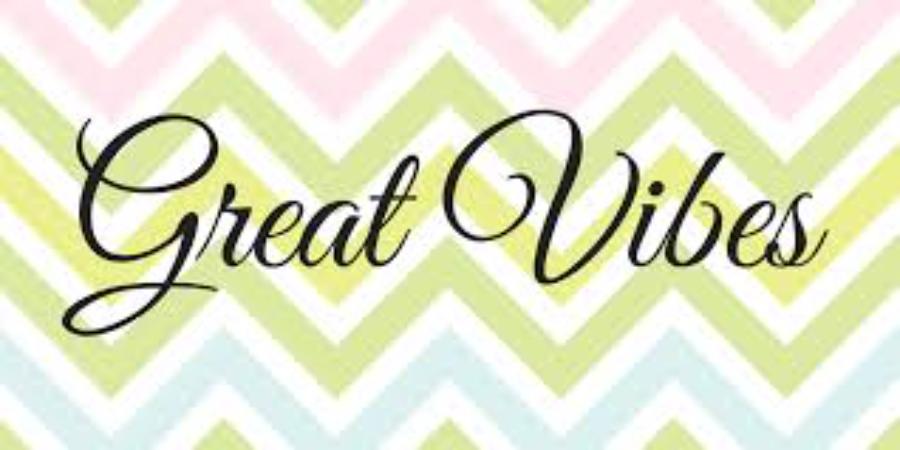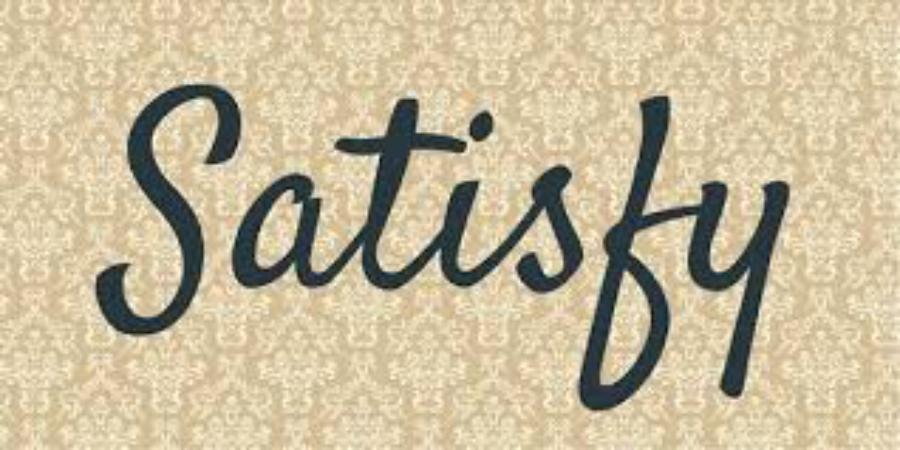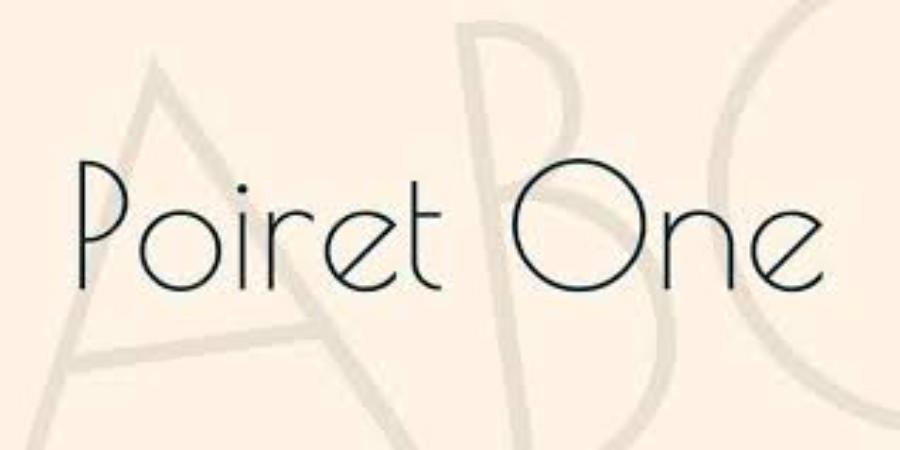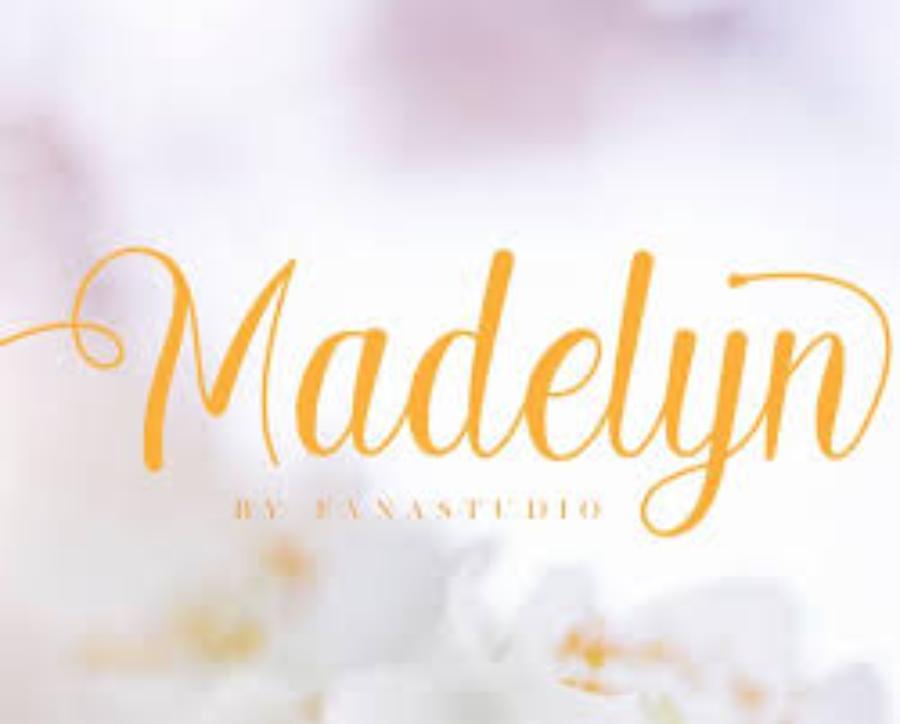
Danh Sách 10 Font Chữ Calligraphy Miễn Phí Bạn Không Thể Bỏ Qua
Danh sách 10 font chữ Calligraphy miễn phí và đẹp mắt cho các designer. Hãy tìm hiểu cách chúng có thể làm phong phú thêm các dự án thiết kế của bạn tại SaDesign.
Lựa chọn font chữ phù hợp là một yếu tố quan trọng quyết định đến tính thẩm mỹ và hiệu quả truyền tải thông điệp trong lĩnh vực thiết kế đồ họa. Font chữ Calligraphy, với vẻ đẹp thanh thoát và sự mềm mại trong từng nét chữ, từ lâu đã trở thành một lựa chọn yêu thích của các designer. Bài viết sau, Sadesign sẽ giới thiệu 10 font chữ Calligraphy miễn phí mà bất kỳ designer nào cũng không thể bỏ qua, giúp bạn tạo ra những tác phẩm thiết kế ấn tượng và chuyên nghiệp hơn.
1. Font chữ Calligraphy là gì?
Font chữ Calligraphy là những kiểu chữ lấy cảm hứng từ nghệ thuật thư pháp, với nét chữ mềm mại, thanh thoát, đầy tính nghệ thuật và trang nhã. Những font chữ này thường được sử dụng trong các dự án thiết kế mang tính trang trọng, lịch lãm như thiệp cưới, thiệp mời, logo, hay các ấn phẩm quảng cáo cao cấp. Một font chữ Calligraphy đẹp không chỉ mang đến sự tinh tế cho thiết kế mà còn giúp truyền tải cảm xúc mạnh mẽ đến người nhìn.
Font chữ Calligraphy không chỉ dừng lại ở những tác phẩm thủ công mà giờ đây, với sự phát triển của công nghệ, các designer có thể dễ dàng áp dụng các font chữ Calligraphy này trong các phần mềm thiết kế như Adobe Illustrator, Photoshop, hay các nền tảng thiết kế online.
2. Top 10 Font chữ Calligraphy miễn phí không nên bỏ qua
Mặc dù có rất nhiều lựa chọn font chữ Calligraphy trên thị trường, nhưng không phải tất cả đều miễn phí. Trong bài viết này, chúng tôi sẽ giới thiệu 10 font chữ Calligraphy miễn phí mà mọi designer đều nên biết.
2.1. Pacifico
Pacifico là một font chữ Calligraphy rất phổ biến với các đường nét mềm mại, uốn lượn tự nhiên. Được thiết kế bởi Vernon Adams, Pacifico có phong cách dễ tiếp cận và rất thích hợp cho các thiết kế mang tính sáng tạo, vui tươi. Font chữ này thường được sử dụng trong các dự án liên quan đến thương hiệu thời trang, quà tặng, và các sản phẩm nghệ thuật.
Ưu điểm:
• Dễ đọc và linh hoạt khi sử dụng.
• Thích hợp cho các thiết kế hiện đại, trẻ trung.
2.2. Great Vibes
Great Vibes là một font chữ Calligraphy tuyệt đẹp với những đường cong mượt mà, thanh thoát. Nó mang đến vẻ đẹp sang trọng và trang nhã, hoàn hảo cho các dự án như thiệp mời, thiết kế logo, hay các ấn phẩm in ấn cao cấp. Great Vibes có sự kết hợp hoàn hảo giữa tính thẩm mỹ và sự dễ đọc, phù hợp với nhiều loại thiết kế khác nhau.
Ưu điểm:
• Phù hợp với các thiết kế sang trọng, quý phái.
• Có thể sử dụng cho nhiều loại dự án khác nhau.
2.3. Allura
Font chữ Allura nổi bật với những nét chữ mềm mại, thanh thoát, mang lại cảm giác rất dễ chịu khi đọc. Sự đơn giản nhưng vẫn đầy tinh tế của Allura làm cho nó trở thành một lựa chọn tuyệt vời cho các dự án cần sự trang nhã mà không quá cầu kỳ. Allura thường được sử dụng trong các ấn phẩm như banner, tờ rơi, hay các thiết kế thương hiệu cần sự lịch lãm.
Ưu điểm:
• Dễ sử dụng và tương thích tốt với các thiết kế website.
• Mang lại vẻ ngoài thanh lịch cho mọi dự án.
2.4. Dancing Script
Dancing Script là một font chữ Calligraphy với phong cách vui tươi, năng động. Những đường nét uốn lượn của Dancing Script khiến nó trở thành lựa chọn lý tưởng cho các thiết kế mang tính cá nhân, sáng tạo và gần gũi. Bạn có thể sử dụng Dancing Script cho các thiết kế như logo, slogan hay quảng cáo sản phẩm.
Ưu điểm:
• Phong cách trẻ trung, linh hoạt.
• Dễ dàng kết hợp với các kiểu chữ khác trong thiết kế.
2.5. Satisfy
Satisfy là một font chữ Calligraphy miễn phí khác, với phong cách mượt mà và sang trọng. Được thiết kế để mang lại sự mềm mại trong từng nét chữ, Satisfy rất phù hợp với các dự án liên quan đến sự kiện đặc biệt như đám cưới, lễ hội, hay các sản phẩm cao cấp. Font chữ này mang đến một cảm giác dễ chịu và rất dễ đọc.
Ưu điểm:
• Mang lại cảm giác mềm mại, dễ chịu cho người nhìn.
• Phù hợp cho các thiết kế với yêu cầu thẩm mỹ cao.
2.6. Kaushan Script
Kaushan Script là một font chữ Calligraphy có thiết kế mạnh mẽ và táo bạo. Được tạo ra với các đường nét phóng khoáng và nổi bật, Kaushan Script rất phù hợp với những dự án thiết kế cần sự nổi bật, thu hút sự chú ý của người nhìn. Đây là một lựa chọn lý tưởng cho các tiêu đề, logo, và các thiết kế quảng cáo.
Ưu điểm:
• Tạo ấn tượng mạnh mẽ ngay từ cái nhìn đầu tiên.
• Phù hợp cho các thiết kế cần sự táo bạo và khác biệt.
2.7. Pinyon Script
Pinyon Script là một font chữ Calligraphy với phong cách cổ điển, mang lại cảm giác sang trọng và thanh thoát. Font chữ này được thiết kế với những nét chữ mềm mại và uốn lượn tinh tế, tạo nên một sự quyến rũ đặc biệt trong các thiết kế. Pinyon Script rất thích hợp cho các dự án thiết kế sang trọng như thiệp cưới, thiệp mời, hay các sản phẩm thủ công cao cấp.